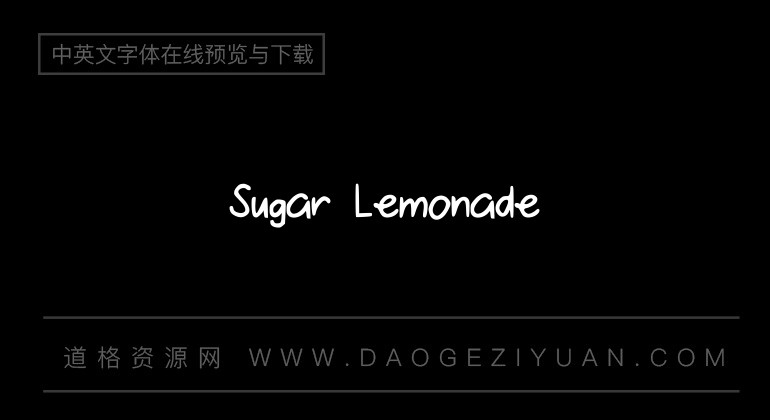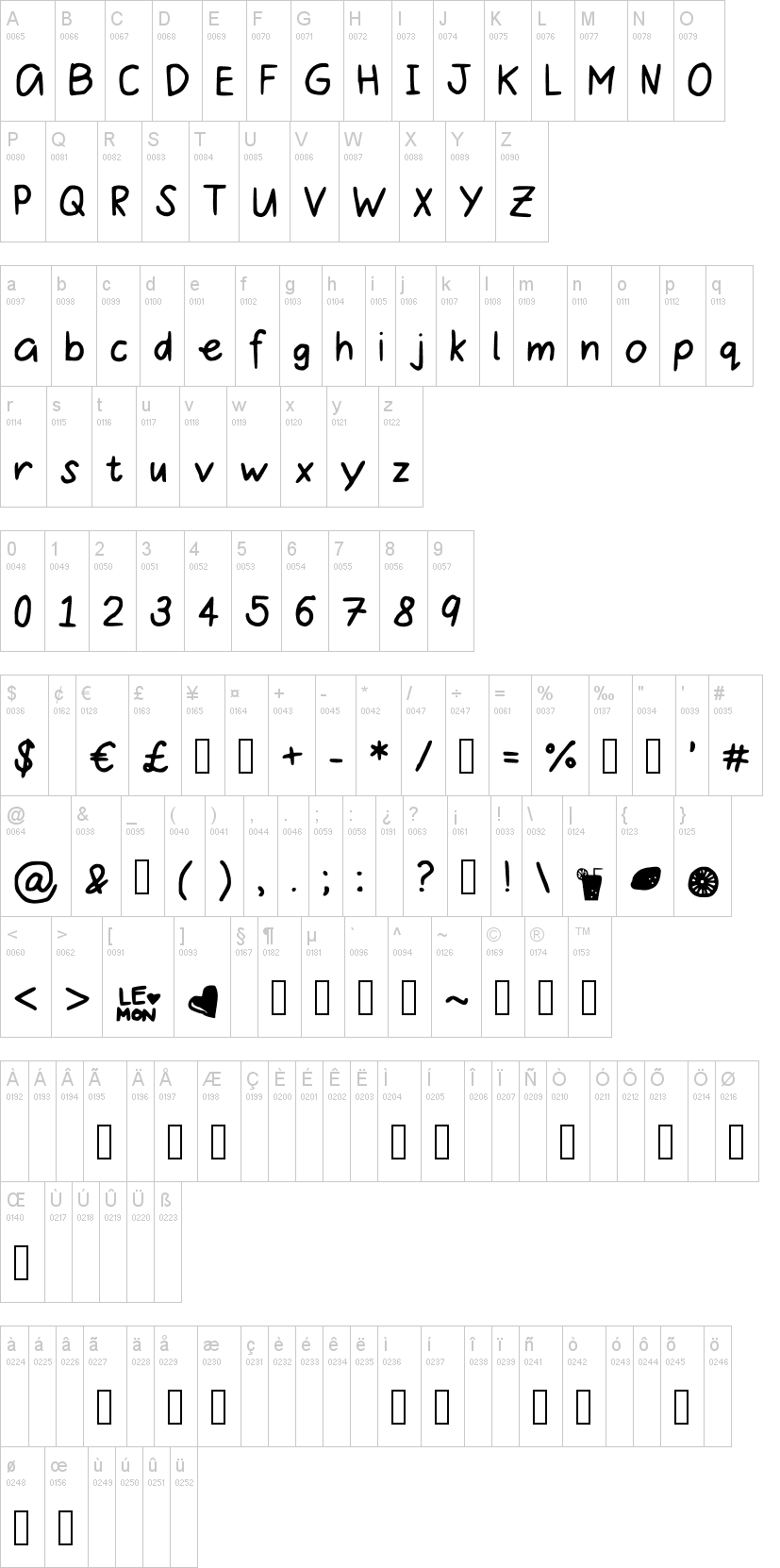
Sugar Lemonade
Sugar Lemonade 是一款充满活力、清新明亮的手写字体,由 Laura Worthington 设计。这个字体的特点是具有自然流畅的笔画和简单优美的线条,它的字形像是用水彩笔书写出来的。 Sugar Lemonade 字体的特点是非常适合应用在印刷品、广告、包装设计、海报等方面。它的应用范围非常广泛。 该字体包括了大写字母、小写字母、数字和标点符号,以及一些特殊符号,例如箭头和星号等。这些字符的设计都非常精致,完美地呈现了手写风格的特点。 总的来说,Sugar Lemonade 字体是一款充满活力、清新明亮的字体,非常适合用于强调品牌的年轻、时尚、自然、亲切等特点。
Sugar Lemonade是一款非常不错的手写艺术字体,具有很好的视觉感,适合于文化类的宣传设计、商业类品牌的广告和产品包装设计以及个性化文字排版等较多场景。
Sugar Lemonade字符映射图